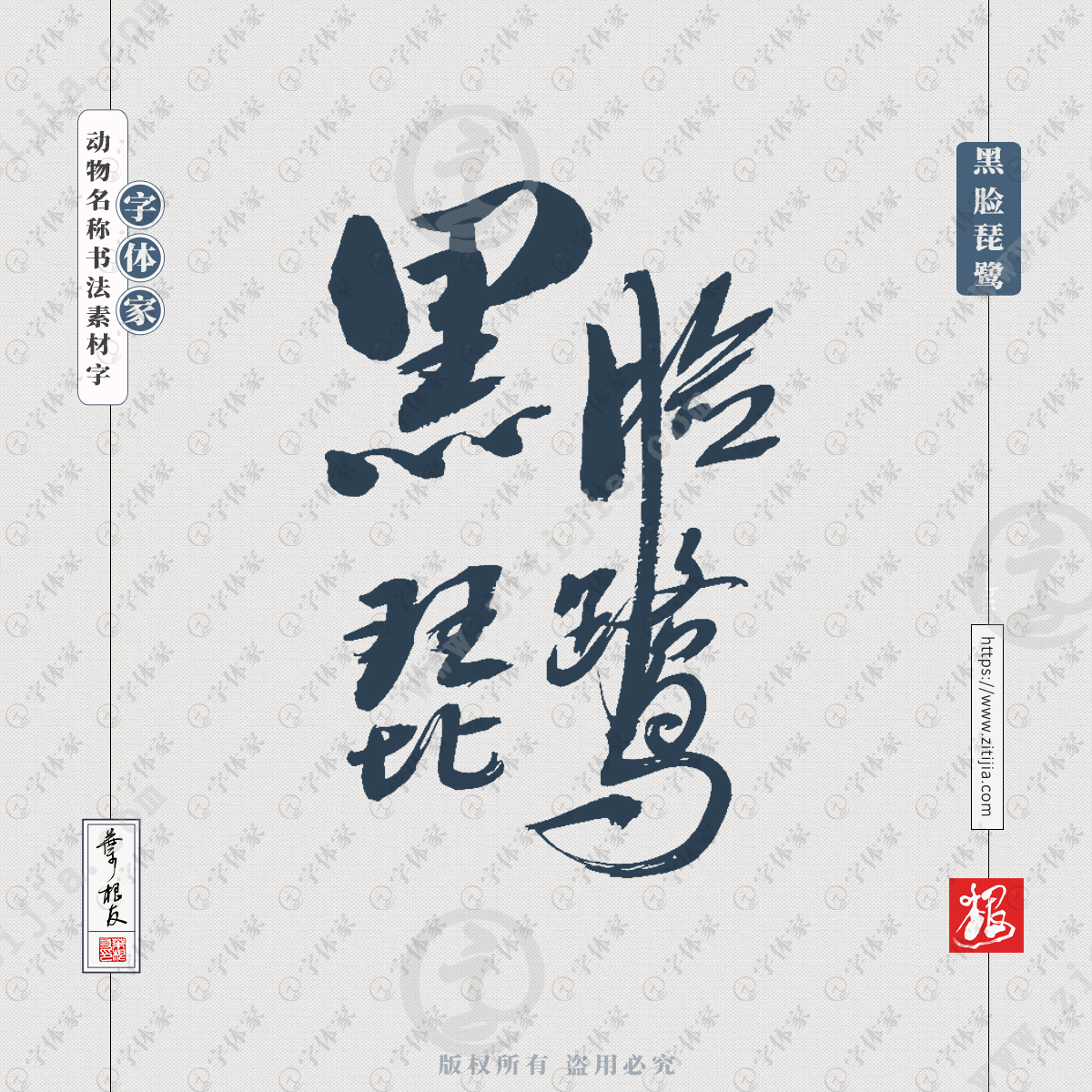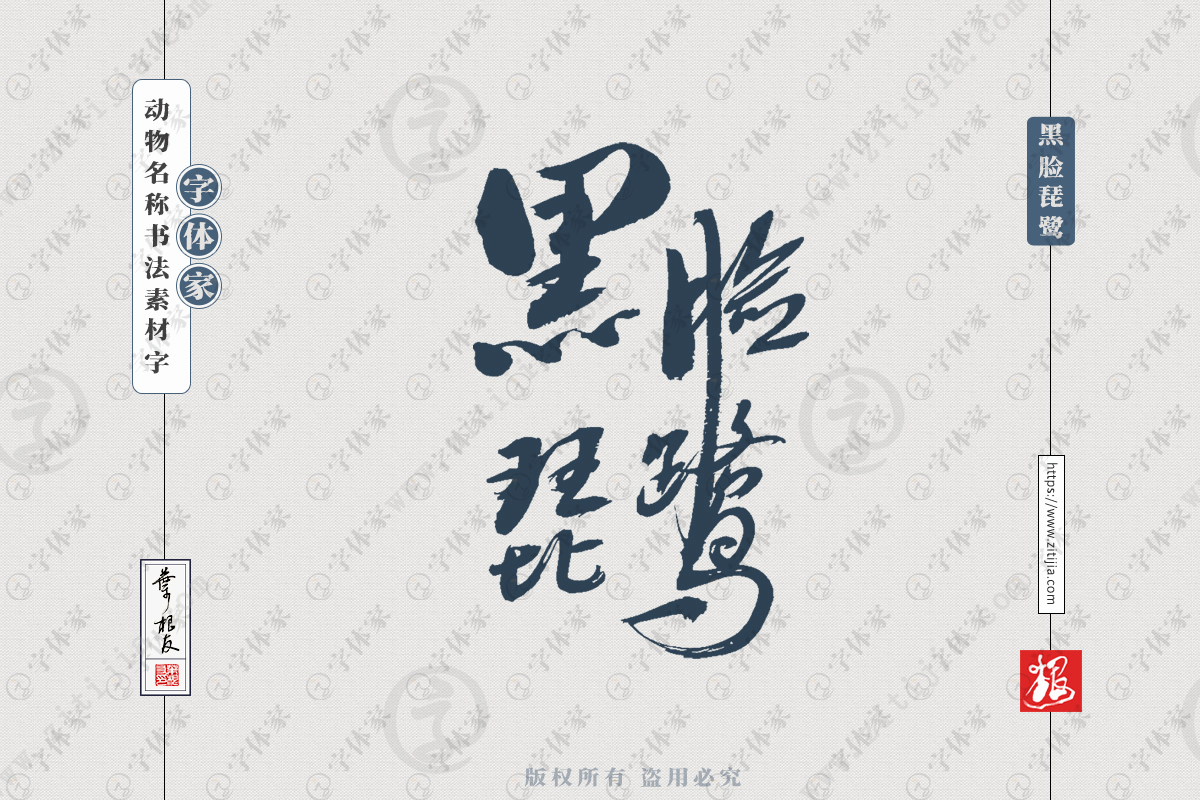
字体家提供黑脸琵鹭手写动物名称叶根友书法素材字体设计可下载源文件
黑脸琵鹭(学名:Platalea minor),又名小琵鹭、黑面鹭、黑琵鹭、琵琶嘴鹭,俗称饭匙鸟、黑面勺嘴,台湾赏鸟人士则俗称为“黑琵”。因其扁平如汤匙状的长嘴,与中国乐器中的琵琶极为相似,因而得名;亦因其姿态优雅,又被称为“黑面天使”或“黑面舞者”;属于鹳形目、鹮科、琵鹭亚科,琵鹭亚科的鸟类全世界共六种,其中以黑面琵鹭数量最为稀少(已知六种琵鹭当中唯黑面琵鹭属濒危物种),属全球濒危物种类别之一。于故当黑面琵鹭在每年10月至翌年2月渡冬时,东南亚观鸟者会到处观测关注其过冬状况并统计数A。黑面琵鹭现时只活跃于东亚及东南亚地区。仅见于亚洲东部,其特征是全身羽毛大体上为白色,有黑嘴和黑色腿、脚,前额、眼线、眼周至嘴基的裸皮黑色,形成鲜明的“黑脸”。